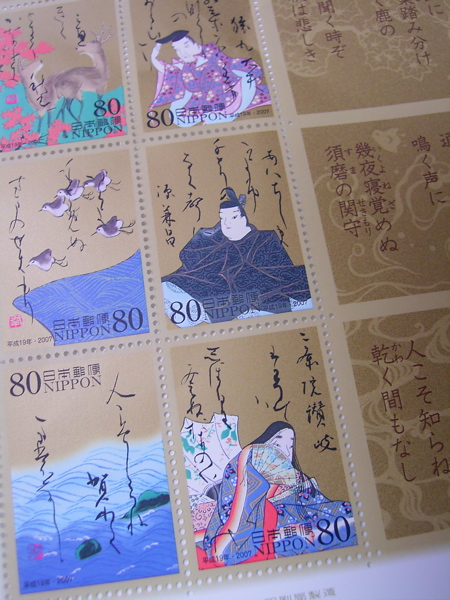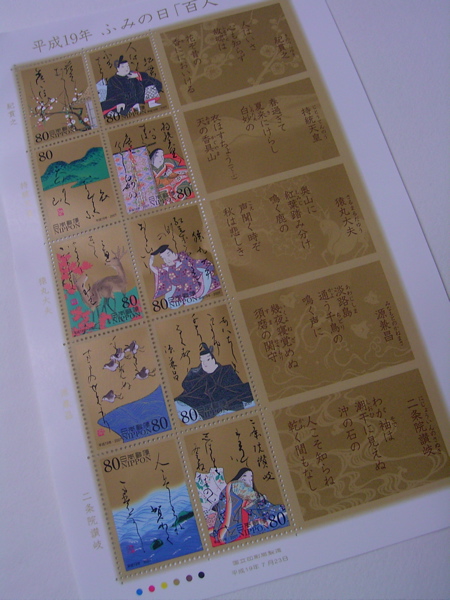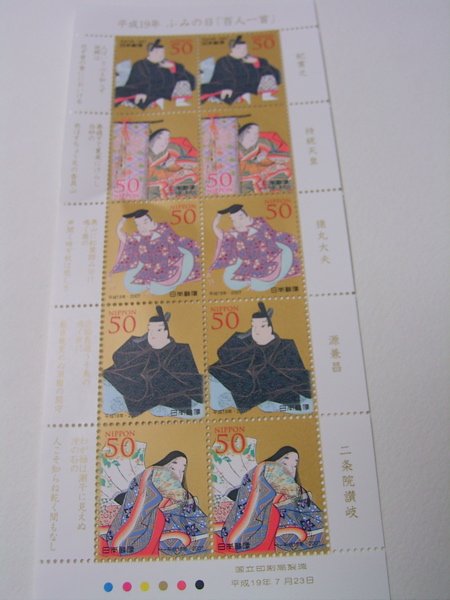
ふみの日 百人一首切手
今日郵便局へ行ったら、新しい記念切手が出ていました。
小さい郵便局だから、記念切手は買っておかないとすぐになくなってしまうので、即ゲット。
なんてったって今回のは文字入り。しかも百人一首。
実は子供の頃、家族でよく百人一首をやっていたので結構強かったのです。(と言っても家族の中でですけど)上の句だけで取るのはもう当たり前。得意な札は絶対に他の人に取られない様にしたり、最初の一文字で取れる札を覚えたり。(む、す、め、ふ、さ、ほ、せ、の文字で始まるのは一つしかない句)
だから、今回の切手の句は興味津々。二条院讃岐の歌の下の句は「ひと」で始まっていますが、この「ひと」で始まる句はたくさんあるので、お手つきしない様に気をつけなければならないのす。
こちらはお姿だけ。
今回の人の中には坊主がいないじゃないですか!
坊主の絵が面白いんですけどね〜。
これら文字はすべて同じ人が書いたのでしょうか。文字好きにとっては、こういう文字を扱った切手はとても嬉しいですよね。
きっと海外のカリグラフィーをやっている人に出したら喜ばれるでしょう。
ブログを読んだ直後もう最寄の郵便局へ向かっていた私。もち、ゲットしました。ほれぼれするほど美しい切手ですね。私も「一字決まり」のカルタは取らねばとむきになるタイプのおなごでした。
百人一首切手、かっこいいですね!
祖母の家にはこういう文字で書かれた百人一首がありました(読めなくて使いませんでしたけど^^;)。
「む」の人は坊主なので…今回の切手のなかにはいないのですね、残念です。